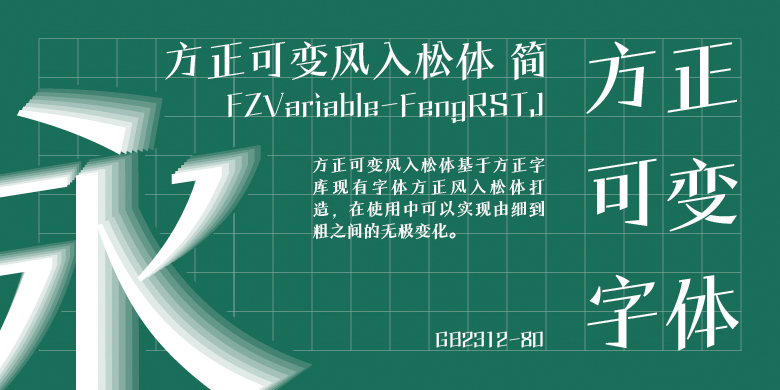
字体名称: 方正可变风入松
方正可变风入松体 简
方正可变风入松体字体支持文字粗细无级调节,设计师通过调整字重轴(Weight)的变化,可以实现字形的平滑连续的细微调整,满足不同版式的设计需求。 风入松体是宋体字的传承与进化,文字笔画的衔接和交叉处给人的视觉反应就是堆墨,镂空的方式本身就很有趣,让这款字体白区贯通,更加透气,象风入松一样高雅灵动,9度的右上倾斜,提振精神,感觉很爽!该字体的应用更侧重于标题字,也许能够起到画龙点睛的作用。